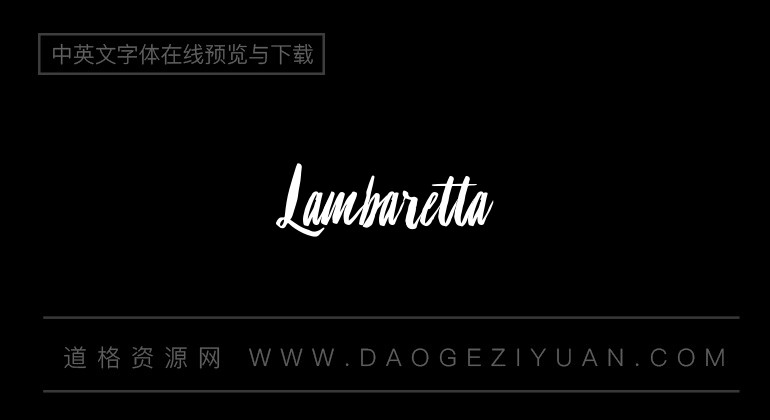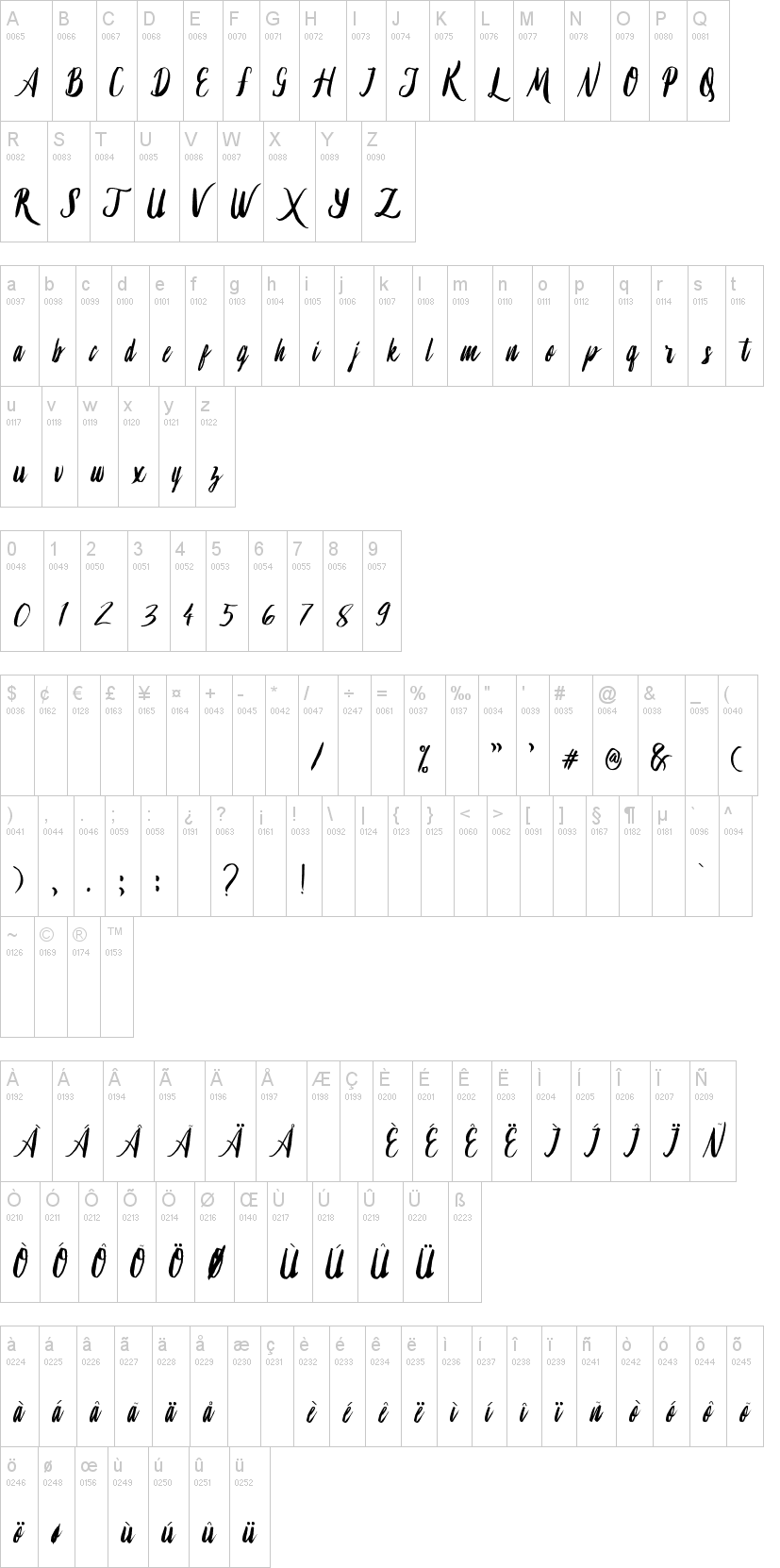
Lambaretta
Lambaretta是一种非常独特且具有艺术风格的字体,它由法国设计师 Fanny Coulez 和 Julien Saurin 设计。Lambaretta的设计灵感来自于20世纪初期的艺术运动,特别是装饰艺术风格。这种字体的特点是柔和、圆润的线条和独特的装饰性元素,使其非常适合用于各种品牌标识、海报、书籍封面等设计作品中。 Lambaretta字体的设计非常独特,它融合了复古和现代的风格,使得它既具有浪漫主义的气息,又不失现代感。Lambaretta字体有两个版本:普通版和粗体版,它们都包含大写字母、小写字母、数字和标点符号,非常适合用于设计不同类型的印刷品。 总的来说,Lambaretta字体是一种非常有个性和艺术感的字体,它的优美线条和独特装饰性元素使得它成为各种设计作品中的不可或缺的元素。
Lambaretta是一款非常不错的手写艺术字体,具有很好的视觉感,适合于文化类的宣传设计、商业类品牌的广告和产品包装设计以及个性化文字排版等较多场景。
Lambaretta字符映射图